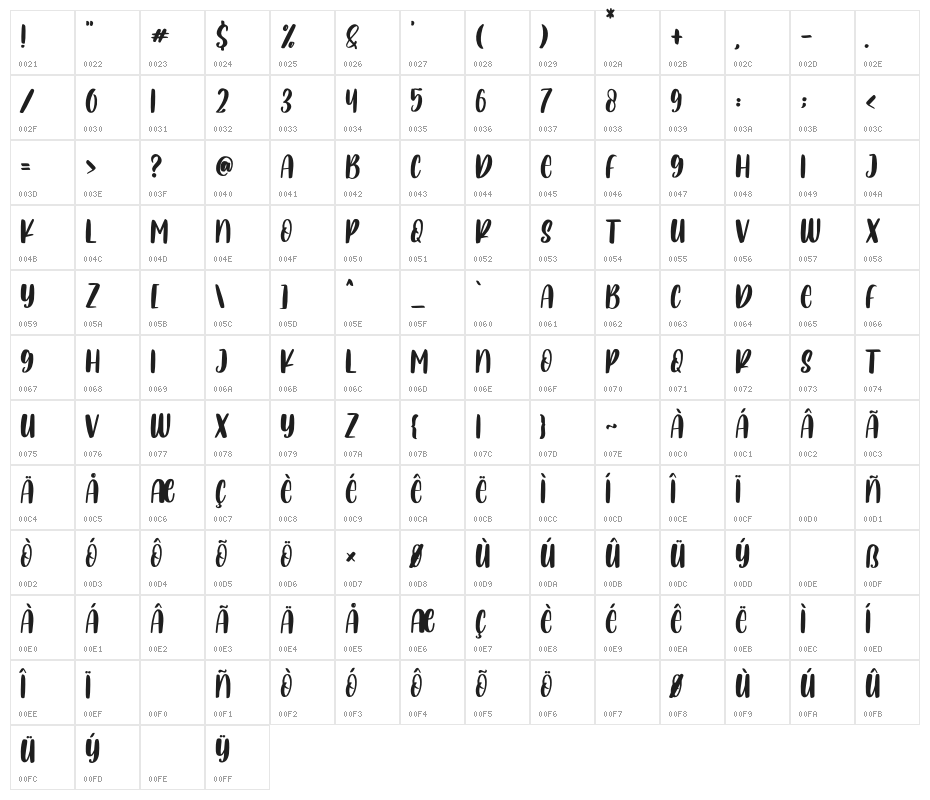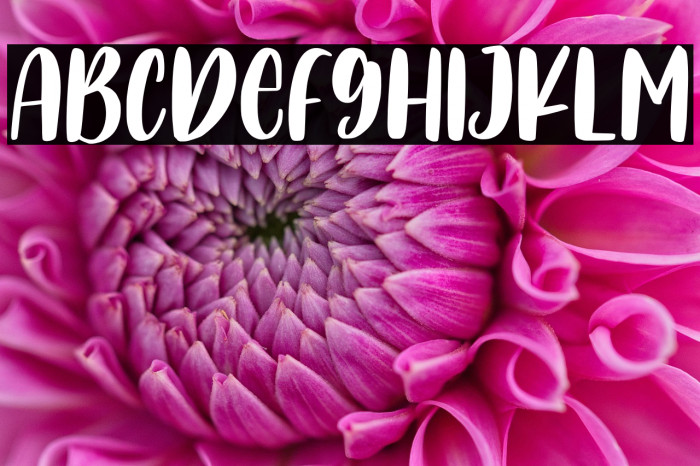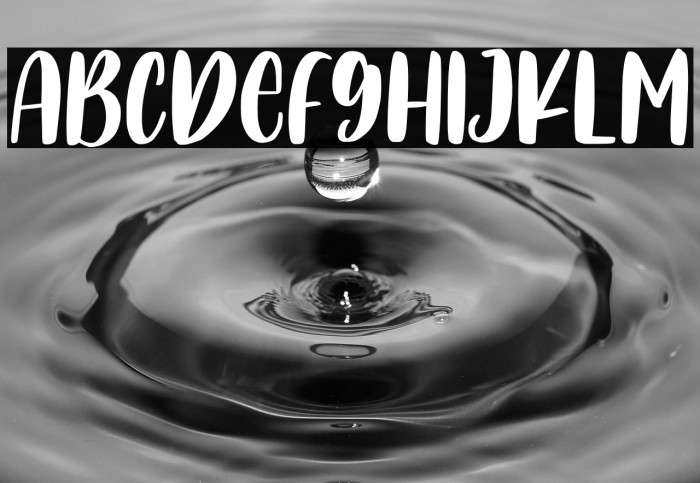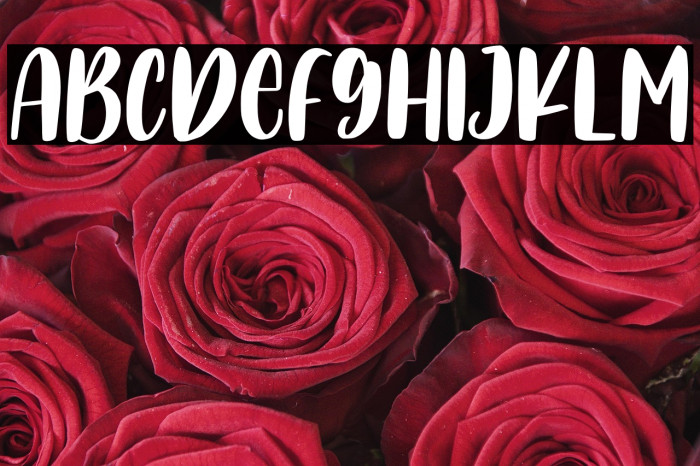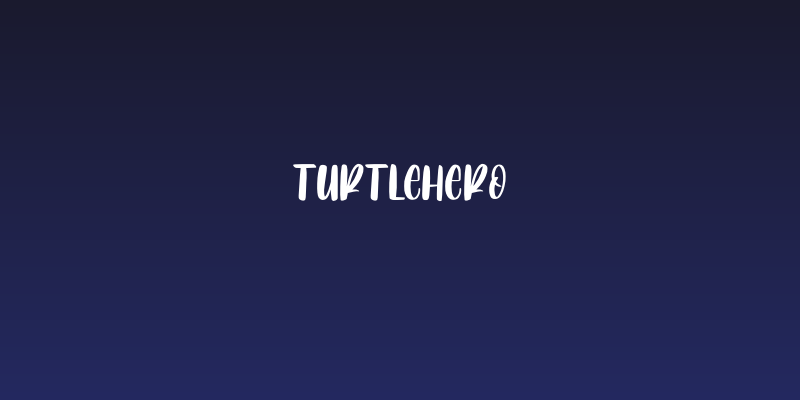
TurtleHero Font
✎ Cartoon
| Categorie | Cartoon |
| Progetti proposti | Ideal for greeting cards, social media graphics, children's book covers, and playful branding projects. |